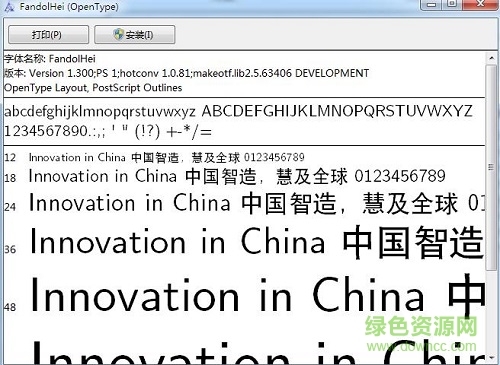
fandol系列字體是一款開(kāi)源了的電腦字體,包括有宋體、黑體、楷體和方體四個(gè)系列,字形各有特色,喜歡的朋友歡迎免費(fèi)下載使用!
Fandol系列字體來(lái)自一家已經(jīng)破產(chǎn)的字體公司,為中國(guó)排版而設(shè)計(jì)的Fandol字體,現(xiàn)在已經(jīng)開(kāi)源了。包含F(xiàn)andolFang、FandolHei、FandolKai、FandolSong四個(gè)字體!